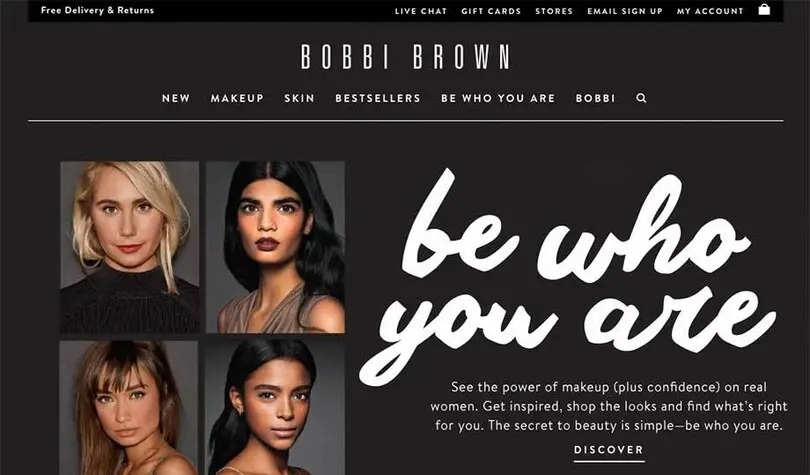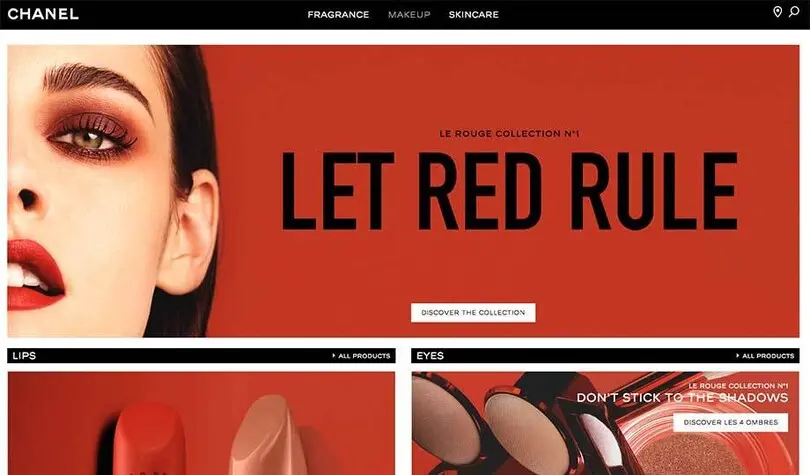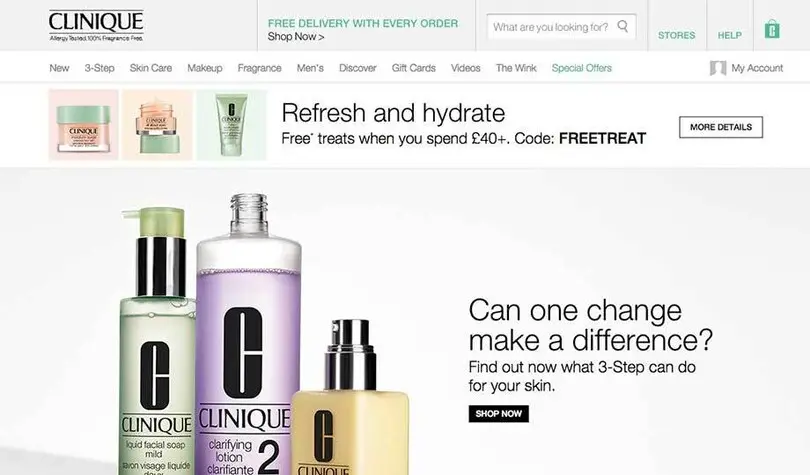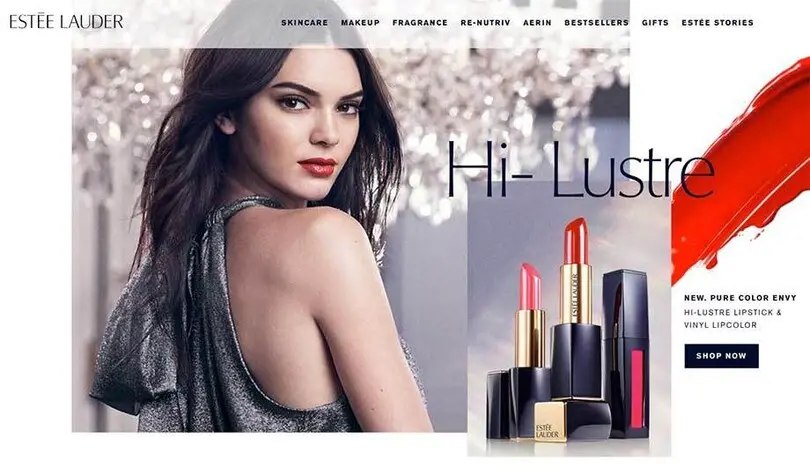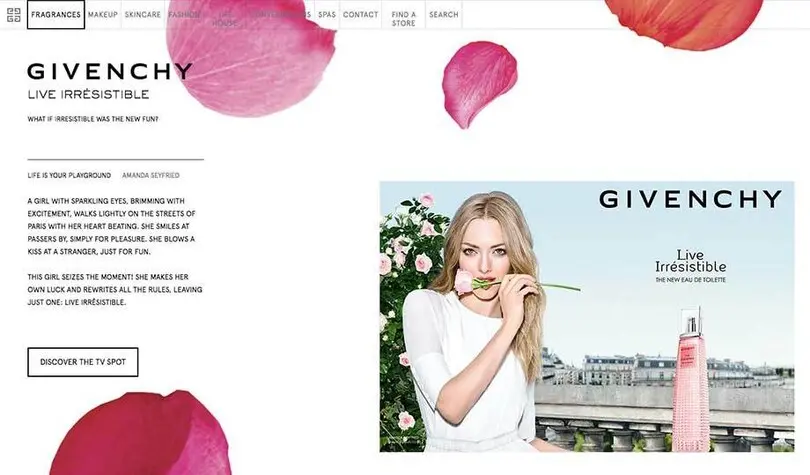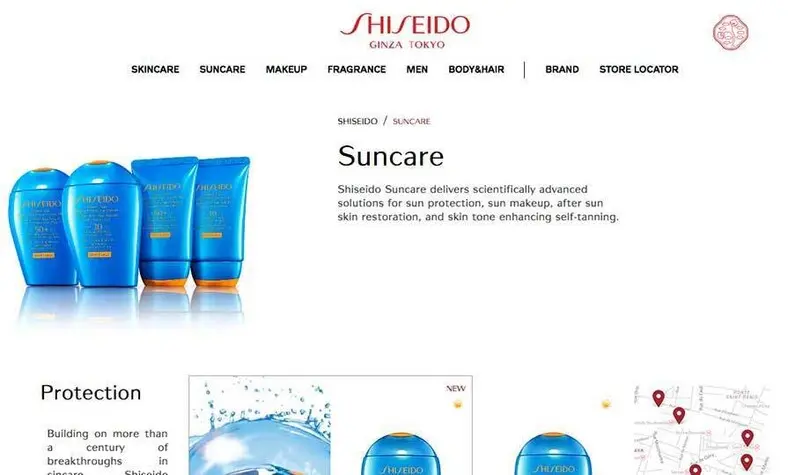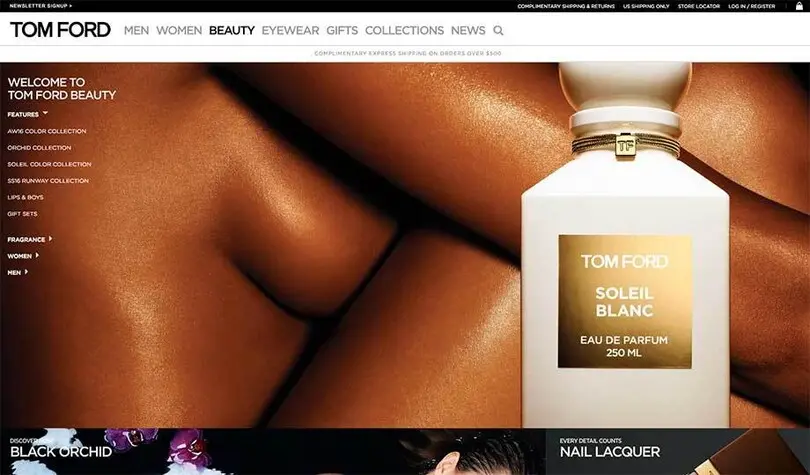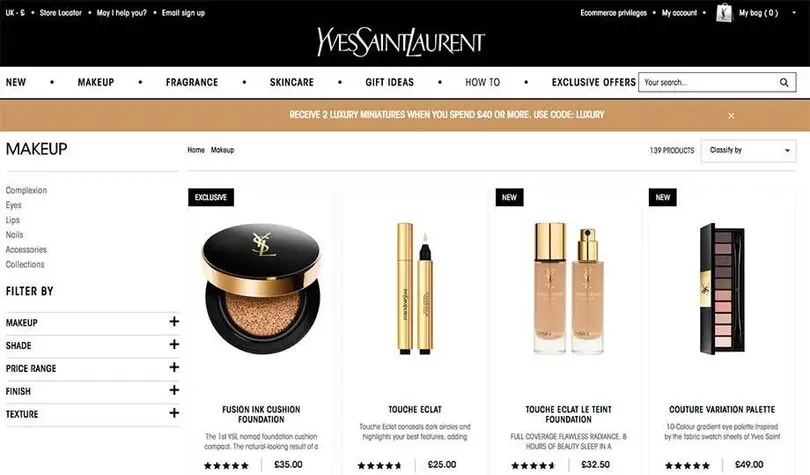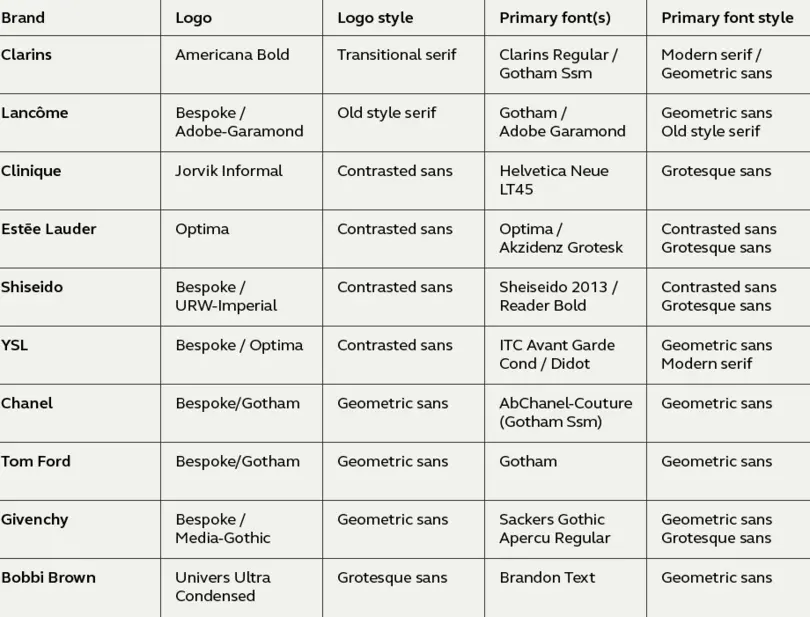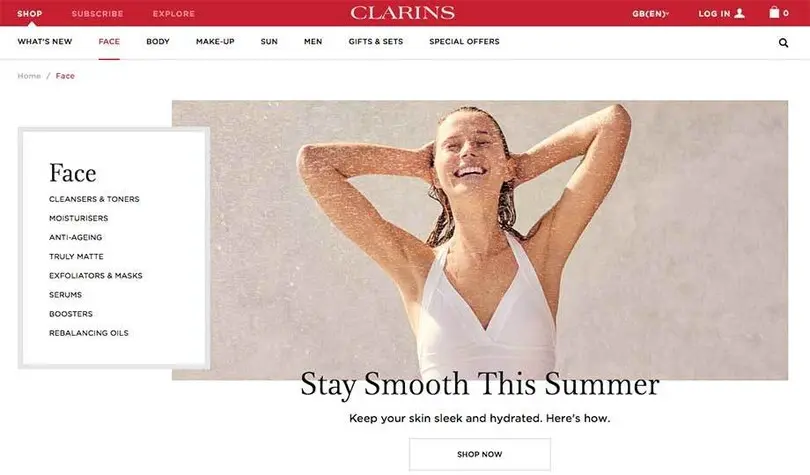
Polices et marques de luxe : la beauté.
Le marché de la beauté se divise clairement en deux catégories : d’un côté, les marques qui recherchent un sentiment d’héritage à travers l’utilisation de polices avec empattements et de forts contrastes ; de l’autre, celles qui adoptent un design plus audacieux et moderne, en s’appuyant sur des polices géométriques et grotesques.
Certaines caractéristiques typographiques sont traditionnellement associées au luxe, comme les empattements et les forts contrastes de traits.
Nous avons mené une étude sur les principales marques de luxe dans les secteurs de la beauté, de la mode et de l’automobile afin d’analyser les polices qu’elles utilisent et leur impact. Premier arrêt : le secteur de la beauté. Toutes les marques utilisent-elles vraiment Optima ? Nous avons examiné dix des plus grandes marques et découvert quelques surprises.
Clarins
La police principale de Clarins est une sérif contrastée proche de Baskerville, une typographie élégante parfaitement adaptée à l’univers des soins et des cosmétiques. La marque mise sur de grands espaces blancs, avec sa police emblématique utilisée pour les titres et Gotham SmartScreen pour le texte courant.
Lancôme
Lancôme perpétue le thème du contraste, avec une version de Garamond aux traits extrêmement fins, exprimant un raffinement absolu. Garamond est utilisée en capitales pour la navigation sur le site web, et en bas de casse pour les titres. Gotham est employée pour les textes courants. La prédominance du noir accentue le contraste, tandis que l’utilisation des couleurs reste très minimaliste.
Clinique
Clinique se distingue par une approche unique. Son logo est basé sur Jorvik Informal, une sérif originale et contrastée. Associée à Helvetica, cette typographie confère à la marque un style épuré, moderne et frais. L’utilisation d’espaces aérés et de tons pastel renforce cet effet minimaliste et efficace.
Estēe Lauder
Optima, une sans serif contrastée, se caractérise par son élégance et sa lisibilité. Estée Lauder l’emploie en faible graisse pour plus de finesse, l’associant à des visuels de grande taille et à un bleu marine institutionnel, conférant une impression à la fois sérieuse et sophistiquée.
Shiseido
Reader Bold, une police proche de Gotham, est utilisée en capitales pour la navigation du site. La marque adopte un thème graphique en noir et blanc, avec une police sur mesure, Shiseido2013, qui rappelle Optima par son fort contraste, sa grande hauteur d’x et ses ouvertures larges. Toutefois, nous avons relevé des problèmes d’alignement sur leur site web, notamment des justifications inégales et un mélange confus d’alignements centrés, justifiés et à gauche.
YSL
Contrairement à l’utilisation massive de Gotham, YSL opte pour ITC Avant Garde Gothic Condensed, une police étroite et monolinéaire peu lisible. La version standard d›ITC Avant Garde Gothic, de style géométrique, est employée en très grande taille, créant un effet dominant qui ne met pas en valeur la finesse de la marque.
Chanel
Le logo de Chanel, une police sans serif géométrique et audacieuse toute en majuscules, incarne l’élégance et le raffinement. La marque utilise une version renommée de Gotham, exclusivement en gras et en majuscules, sauf pour le texte courant en Helvetica. La distinction entre les gammes masculines et féminines repose uniquement sur la couleur et l’imagerie.
Tom Ford
Sur le site de Tom Ford, l’utilisation exclusive des majuscules et un thème noir et blanc créent une ambiance forte, audacieuse et résolument moderne. Cette approche séduit un public jeune, en quête de style et de confiance, tout en véhiculant une image très masculine et dominante.
Givenchy
Givenchy, marque de luxe française au style chic et créatif, favorise l’image plutôt que le texte. Cependant, elle utilise des majuscules dans tout son univers visuel. Sackers Gothic Light, une police monolinéaire étendue, y côtoie Apercu, une grotesque aux proportions étroites, créant un contraste avec l’emblème carré de la marque.
Bobbi Brown
Le logo de Bobbi Brown repose sur Univers Ultra Condensed, seul exemple d’utilisation de proportions étroites parmi les marques étudiées. L’identité visuelle se construit autour de forts contrastes noir et blanc, avec une typographie manuscrite qui manque de précision. L’emploi de Brandon Text, une sans serif géométrique arrondie, adoucit l’ensemble mais paraît flou à certaines tailles.
Tendances et conclusions.
L’élégance s’écrit en gras
Contrairement à l’idée reçue selon laquelle les marques de beauté choisissent uniquement des polices fines et délicates avec empattement, un nouveau mouvement se dessine. Nous observons une adoption croissante de styles monochromes, audacieux et en majuscules. Ces polices ne se limitent plus aux logos, mais s’étendent à la navigation et parfois même au texte courant
Une police sans sérif contrastée peut être tout aussi élégante qu’une police avec empattement, à condition qu’elle soit bien exécutée – l’exemple d’Estée Lauder avec Optima en est une parfaite illustration. Se démarquer dans ce secteur saturé peut être difficile, c’est pourquoi le choix de la police et du logotype devient d’autant plus crucial.